DVN Barcelony Việt Hoá - Font chữ Script đẹp mắt để làm chữ ký
Là một Designer, chắc hẳn bạn đã nhiều hơn một lần sử dụng font Script cho các sản phẩm sáng tạo của mình. Font Script là font chữ đẹp và được sử dụng nhiều. Nhưng nếu như bạn chỉ mới bắt đầu con đường thiết kế của mình và chưa có nhiều thông tin về font Script hay có cho mình những bộ Script font Việt hóa đẹp thì bài viết này chính là dành cho bạn. 3DKIDGRAPHIC xin giới thiệu sơ lược về DVN Barcelony Việt hoá - Font chữ Script đẹp mắt để làm chữ ký và gửi đến các bạn link download font Script Việt hoá miễn phí ở cuối bài
1. Font Script là gì?
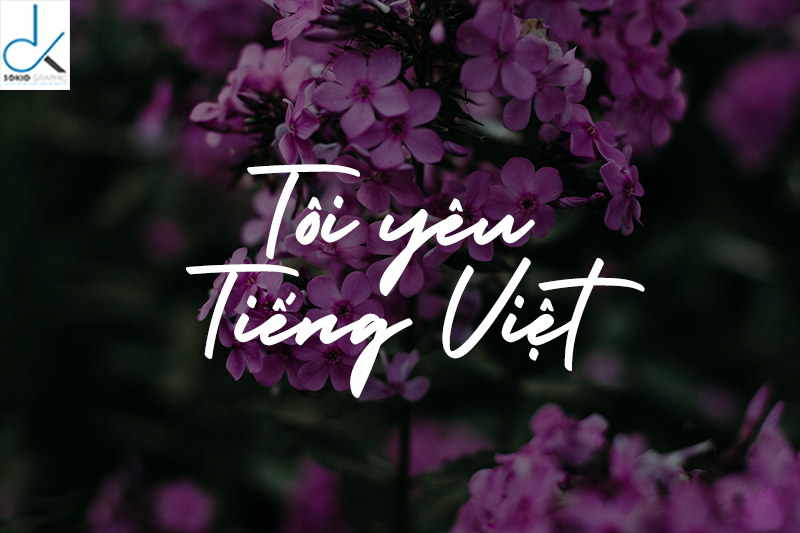
Font Script
Font Script là font chữ có cấu trúc mảnh và được làm nổi bật bởi các đường cong như hình vẽ. Tuy nhiên font chữ này sẽ khá là khó sử dụng và có một vài hạn chế nhất định trong các thiết kế dùng cho in ấn.
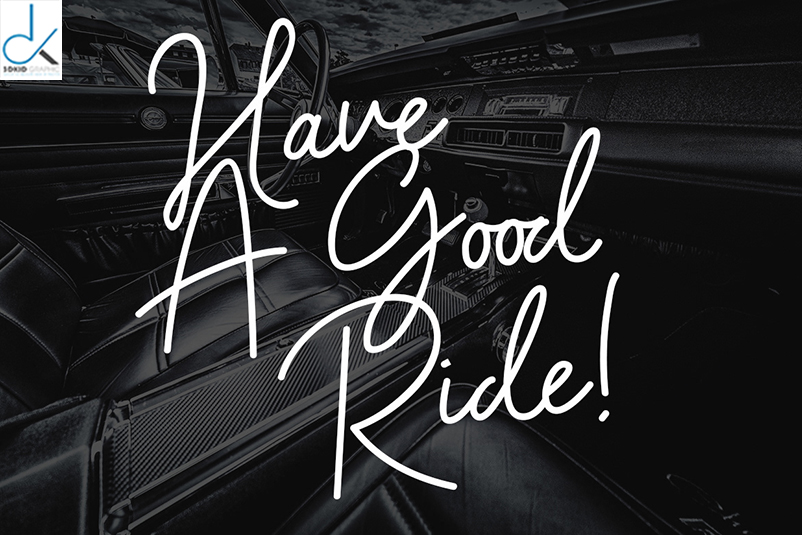
Font Script
Sử dụng quá nhiều font Script cho nội dung văn bản sẽ khiến nó trở nên rối mắt và khó đọc, gây khó chịu cho người nhìn. Mẫu font này thường được dùng trong các loại thiệp mời đám cưới, bìa sách lãng mạn, poster phim,...
2. Top 10 Mẫu Font Script đẹp mắt bạn nên biết
Font Script - Amarillo
Đây là 1 font chữ thư pháp được Francis Studio thiết kế. Nó rất phù hợp cho tiêu đề thiệp cưới hoặc văn phòng phẩm nhờ sự sinh hoạt và các nét đơn giản của nó. Font chữ này sẽ hoàn hảo hơn nếu được kết hợp cùng các font Serif cổ điển như EB Garamond.
Font Script - Blacksword
Blacksword là một phông chữ script sắc nét có tính năng swifelike swashes được thiết kế bởi Youssef Habchi. Kiểu chữ này được sử dụng tốt nhất làm tiêu đề có kích thước lớn, vì các dấu gạch ngang có thể khó đọc ở kích thước nhỏ. Nó sẽ trở nên hoàn hảo hơn kết hợp cùng một font sans serif như Nunito.
Font Script - Broadcast Matter
Thêm một liên lạc viết tay vào thiết kế của bạn với phông chữ tập lệnh brush có texture này. Broadcast Matter sẽ đẹp hơn khi đi với một font serif như Source Serif Pro.
Font Script - Dancing Script
Dancing Script được thiết kế bởi Impallari Type, bắt chước các chuyển động của một vũ công chuyên nghiệp, thanh thoát và uyển chuyển. Khi Dancing Script đi cùng với font Sans Serif như Lato sẽ cho một sự tương phản vui tươi.
Font Script - Francisco
Phông chữ Francisco do Premier Graphics nắm quyền sở hữu. Đây là một phông chữ có đường nét vẽ tay rất thích hợp để làm chữ ký.
Font Script - Golden Plains
Golden Plains, được sản xuất bởi BLKBK Fonts, tạo ra một cảm giác ma mị, kỳ quái với họa tiết tinh tế và dạng chữ hữu cơ.
Font Script - Great Vibes
Great Vibes, một font script tinh tế, tao nhã được sản xuất bởi TypeSETit.
Font Script - Julietta
Font chữ này do StereoType thiết kế và sở hữu. Những chữ cái có các đường nét dày nổi bật dựa trên những cảnh quan rừng nên thơ và mơ mộng.
Font Script - Mark My Words
Font chữ brush này cũng do StereoType thiết kế và có các ký tự chữ dày được vẽ bằng một dấu Stabilo. Mark My Words với kết cấu tinh tế có hiệu ứng vẽ tay nên hoàn hảo cho việc kết hợp với các nền ảnh chủ đề du lịch, khám phá.
Font Script - Matsury
Phong cách kịch bản chữ ký của Matsury thể hiện rất đẹp khi áp dụng cho hình ảnh nền hoa để tạo cảm giác sang trọng, đẳng cấp.
Barcelony là một kiểu chữ ký đơn giản và thanh lịch. Barcelony hoàn hảo cho các dự án xây dựng thương hiệu, logo, thiết kế trongđám cưới, bài đăng trên mạng xã hội, quảng cáo, bao bì sản phẩm, thiết kế sản phẩm, nhãn, nhiếp ảnh, thư mời, văn phòng phẩm và bất kỳ dự án nào cần hương vị chữ viết tay.